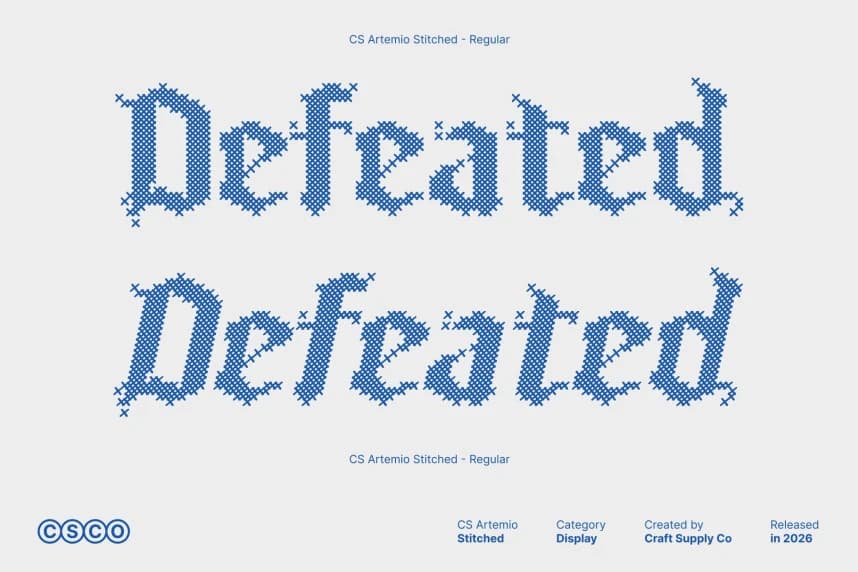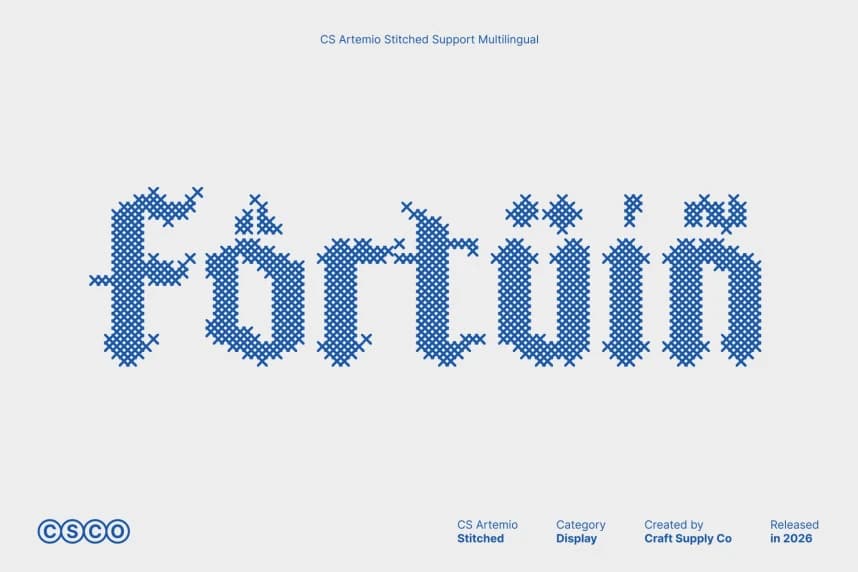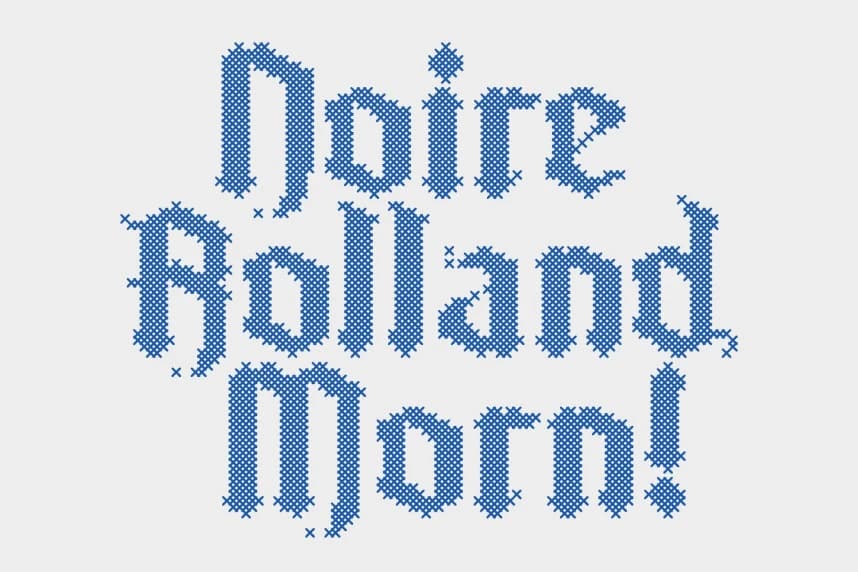
CS Artemio Stitched Font
CS Artemio Stitched Font – Blackletter Font: Orta Çağ Zarafeti ve Güçlü Bir Görsel Varlık; Gothic Blackletter ile El Yapımı Karakter. Bu, Orta Çağ zarafeti ve otoritesinin özünü yakalayan bir Blackletter Gothic display serif yazı tipidir.
CS Artemio Stitched Font – Blackletter Font: Güçlü bir görsel etkiye sahip Orta Çağ zarafeti Gothic Blackletter ile el yapımı karaktere sahip. Bu, Orta Çağ zarafeti ve otoritesinin özünü yakalayan bir Blackletter Gothic gösterişli serif yazı tipidir.